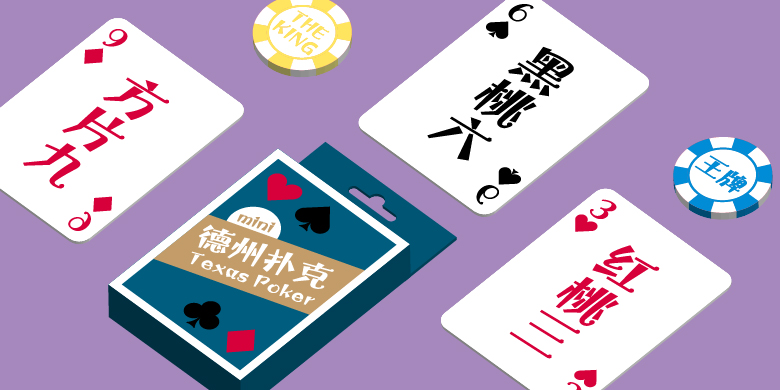
方正宝城体家族
方正宝城体家族,这款字体结构工整、笔画清晰,兼顾美观与易读性,适用于标题、正文、海报、包装、LOGO 等多种场景。字形优雅稳定,风格百搭耐看,适配日常排版与创意设计,让文字呈现更舒适、更具质感。方正宝城体家族一笔一画,皆是细节,以均衡的比例、流畅的线条打造舒适视觉体验,字形端正大气,风格简约现代。无论是商业设计、品牌宣传还是日常排版,都能轻松驾驭,让文字更有格调与力量。方正宝城体家族字体下载。
方正宝城体家族:宝城体在右斜的横画、竖弯钩等笔画上增设小圆点,加上爽利跳跃的笔画组合,使得文字充满活力和趣味性。
适合年青人品牌、体育用品、儿童玩具等包装设计和商业宣传。